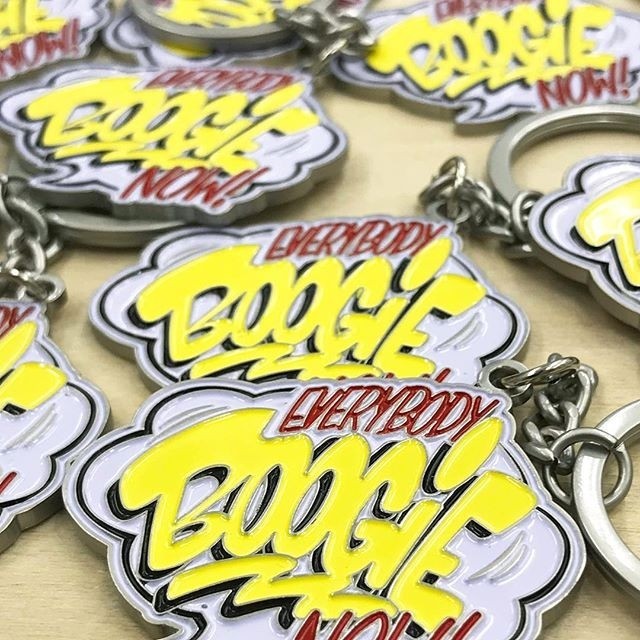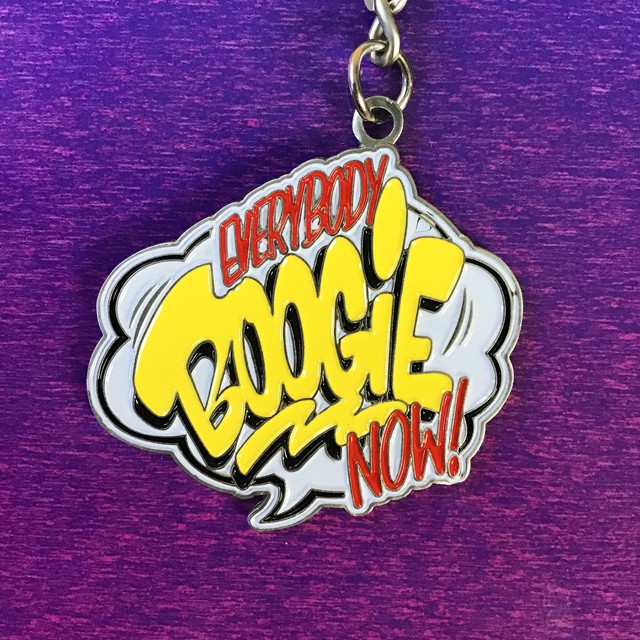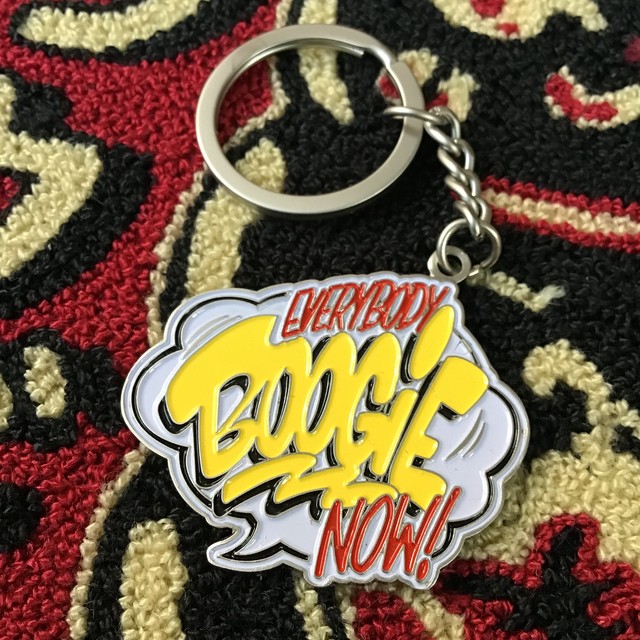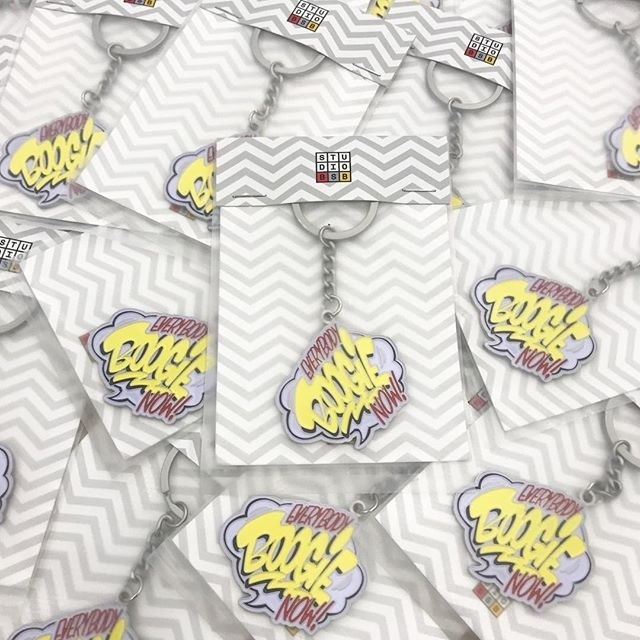
STUDIO BSB - EVERYBODY "BOOGIE" NOW KEYCHAIN
香港発のSTUDIO BSB。世界中で人気のGraffiti Writerとのコラボで人気です。ピンバッジやキーチェーンなどの小物はセレクティブでセンスが良く、今まで店頭に並べるとすぐに売り切れてしまっています。スイスとドイツを拠点に活動するBOOGIEらしいレターデザインで丈夫なメタリックのキーチェーンです。バッグや小物入れおケースに付けておくと目立つこと間違いなし! 数量限定の生産です。
Everybody Boogie Now keychain by Boogie.